Fraktur Schrift Generator: Altdeutsche Schrift kopieren & einfuegen
Ich sass mal drei Stunden lang in einem Discord-Server und hab mir ueberlegt, warum mein Nutzername so aussieht wie jeder andere. Max_Gamer_99. Kreativ wie ein leeres Dokument. Alle hatten denselben generischen Look – fett, kursiv, maximal ein Sternchen vorne und hinten. Dann hat jemand in meinem Server etwas reingeschrieben, das aussah wie aus einem mittelalterlichen Manuskript. TeamLeader in Fraktur. Ich hab sofort gefragt, wie das geht. Die Antwort war einfacher als erwartet: ein Fraktur Schrift Generator, kostenlos, direkt im Browser.
Seitdem nutze ich Frakturschrift fuer alles, was auffallen soll. Gaming-Namen, Discord-Rollen, WhatsApp-Statusmeldungen, manchmal sogar Instagram-Bios. Die Reaktionen sind jedes Mal dieselben – Leute fragen, wie ich das gemacht hab. Wer Fraktur richtig einsetzt, wirkt sofort anders als alle anderen. Nicht ueberdesigned. Einfach charakterstark.
In diesem Artikel erklaere ich, was Frakturschrift wirklich ist, warum sie heute auf Social Media und in der Gamingszene so einen Run erlebt, wie du sie in Sekunden fuer WhatsApp, Instagram oder PUBG-Profile nutzt – und welche Stile sich wofuer eignen. Kein Designstudium noetig. Nur Copy, Paste, fertig.
Was ist Fraktur und warum sieht sie so anders aus
Frakturschrift ist eine gebrochene Schrift – die Buchstaben bestehen aus kantigen, abgeknickten Strichen statt aus runden Kurven. Das Wort Fraktur kommt vom lateinischen fractura, was Bruch bedeutet. Genau das sieht man: Buchstaben, die an bestimmten Stellen brechen statt fliessen.
Entstanden ist sie im fruehen 16. Jahrhundert im deutschen Sprachraum. Bis weit ins 20. Jahrhundert war Fraktur die dominante Druckschrift in deutschsprachigen Laendern – in Buechern, Zeitungen, Urkunden. Wer heute alte Familienfotos oder historische Dokumente aus der Vorkriegszeit aufschlaegt, sieht fast immer Fraktur.
Heute interessiert die meisten Menschen die Geschichte weniger als die Optik. Fraktur wirkt gleichzeitig historisch und edgy. Das macht sie zur perfekten Schrift fuer Gamertags, Metal-Merch, Tattoo-Vorlagen und Instagram-Bios, die aus der Masse herausstechen sollen. Die moderne Version basiert auf Unicode – einem globalen Zeichenstandard mit ueber 149.000 Zeichen, darunter zwei vollstaendige Fraktur-Alphabete.
Fraktur vs. Fett-Fraktur: Die zwei wichtigsten Stile
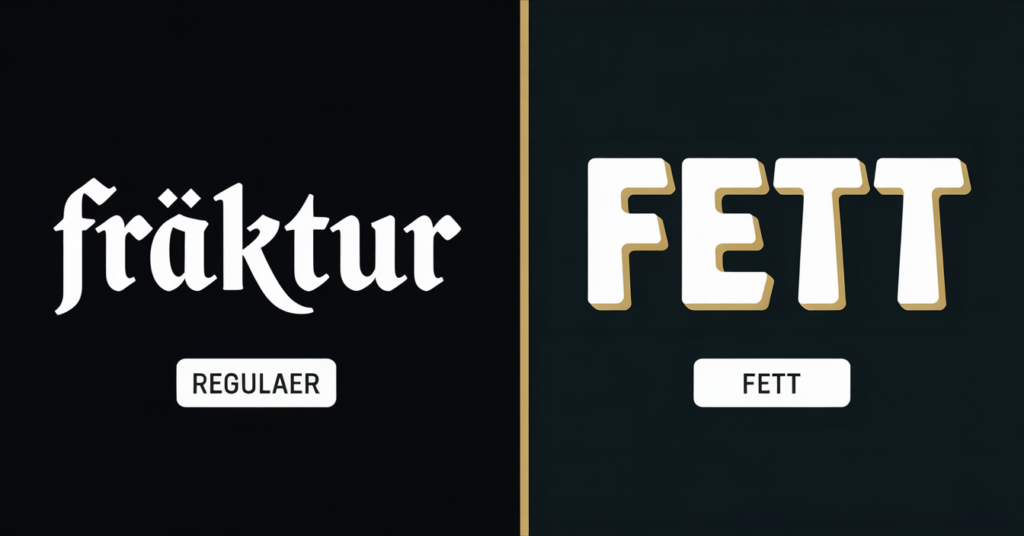
Wer mit einem Fraktur Schrift Generator arbeitet, begegnet zwei Hauptvarianten. Der Unterschied ist klein, aber sichtbar.
Regulaere Fraktur: schlanker, historischer, eleganter Look. Die Buchstaben haben Luft. Gut fuer Bios, Zitate, Unterschriften.
Fette Fraktur: massiver, aggressiver, sofort auffaellig. Die Striche sind breiter. Gaming-Profile, Discord-Namen, PUBG-Clantags – hier gehoert fette Fraktur hin.
Tipp aus der Praxis: Kurze Namen und Begriffe funktionieren mit Fraktur deutlich besser als lange Saetze. TeamLeader in Fraktur wirkt stark. Drei Absaetze in Fraktur werden schnell unleserlich. Fraktur ist eine Akzentschrift – nicht fuer Fliestext.
Was dabei entsteht, sind keine Bilder – es ist reiner Text aus Unicode-Zeichen. Das bedeutet er ist durchsuchbar, teilbar und funktioniert auf praktisch jedem Geraet weltweit.
Fraktur auf Instagram: Bio, Captions, Highlights
Instagram erlaubt keine echte Schriftartaenderung. Wer aber Unicode-Fraktur einfuegt, sieht sofort den Effekt – weil Instagram Unicode-Zeichen darstellt wie normalen Text, nur halt mit einem voellig anderen Look.
Am besten funktioniert Fraktur in der Instagram-Bio. Ein Name in fetter Fraktur, ein kurzer Claim in regulaerer Fraktur – das wirkt professionell und originell zugleich. Creator und Influencer nutzen das seit Jahren, weil es keine App-Kosten verursacht und trotzdem sofort auffaellt.
Fuer Captions empfiehlt sich Fraktur sparsam. Ein Wort zur Betonung, ein Zitat als Abschluss. Ganze Captions in Fraktur werden auf dem Handy schwer lesbar – besonders fuer aeltere Geraete, deren System bestimmte Unicode-Zeichen als Kaestchen darstellen kann.
Fraktur fuer Gaming: PUBG, Discord, Fortnite, Roblox